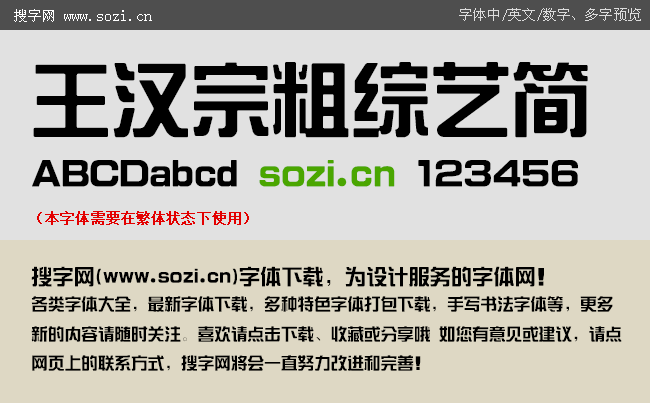
王漢宗粗綜藝簡(jiǎn)
搜字網(wǎng)提供一款王漢宗粗綜藝簡(jiǎn)下載。綜藝體是黑體的一種變體,也是藝術(shù)字的一種。特點(diǎn)是筆劃更粗,盡量將空間充滿。同時(shí)為了美觀,對(duì)拐彎處的處理較為圓潤(rùn)。適用于廣告、報(bào)刊等的標(biāo)題及海報(bào)展板等設(shè)計(jì)場(chǎng)合使用。